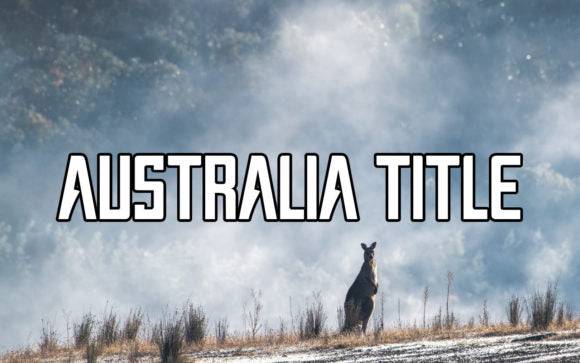
Fuente de título de Australia para Cricut, Silhouette y diseños imprimibles
Australia Title es una impresionante fuente sans serif. Sus caracteres son hermosos y equilibrados, por lo que combina con una amplia gama de diseños. ¡Añádela a tus ideas más creativas y observa cómo las hace realidad!
- Estilo sans serif
- Personajes bien equilibrados
- Versátil para varios diseños.